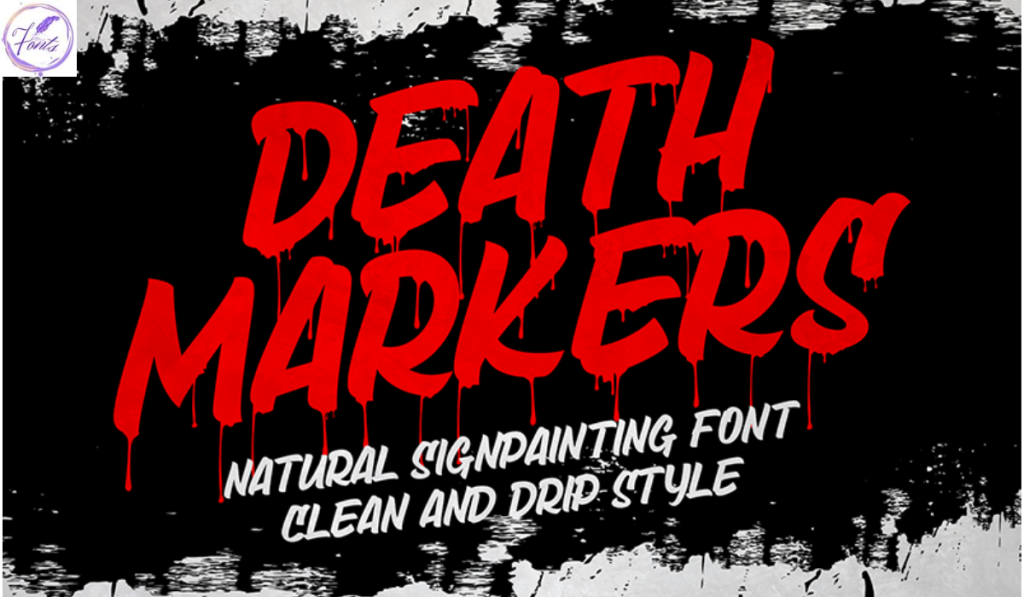
Font chữ death markers việt hóa
Tác giả: Figuree Studio
Ngày phát hành: 2024
Ngôn ngữ: Tiếng Việt, Tiếng Anh, và nhiều ngôn ngữ khác
Bộ Font: Death Markers
Phân loại: Kinh dị, Vintage, Cọ vẽ
Kiểu chữ: sans serif, script
Font chữ death markers là một lựa chọn hoàn hảo cho những ai muốn tạo ra các thiết kế mang phong cách rùng rợn và bí ẩn. Được ra mắt vào năm 2024 bởi Figuree Studio, font này nhanh chóng trở thành một trong những lựa chọn yêu thích cho các dự án liên quan đến Halloween, phim kinh dị, và các sự kiện đặc biệt. Với các đường nét sắc nhọn và kiểu dáng độc đáo, font chữ death markers giúp tạo nên không khí rùng rợn nhưng không kém phần nghệ thuật. Hơn nữa, font này đã được Việt hóa hoàn toàn, giúp bạn dễ dàng sử dụng trong các thiết kế tiếng Việt mà không gặp khó khăn về hiển thị ký tự.
Đánh giá font chữ death markers
Font chữ death markers nhận được nhiều đánh giá tích cực từ cộng đồng thiết kế. Nhiều nhà thiết kế đã sử dụng font này cho các dự án của họ và khen ngợi nó vì khả năng tạo cảm giác mạnh mẽ và cuốn hút. Các tạp chí thiết kế uy tín cũng đánh giá cao font chữ death markers về tính ứng dụng và thẩm mỹ. Font chữ này không chỉ đẹp mắt mà còn rất dễ sử dụng, phù hợp cho cả thiết kế in ấn và kỹ thuật số. Nếu bạn đang tìm kiếm một font chữ rùng rợn để làm mới dự án của mình, font chữ death markers chắc chắn sẽ là lựa chọn tuyệt vời.